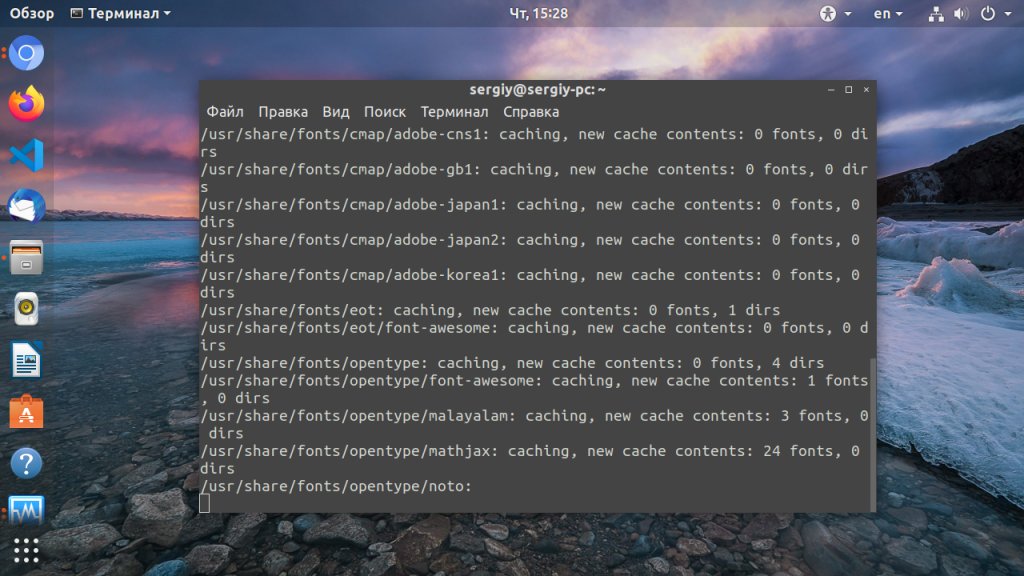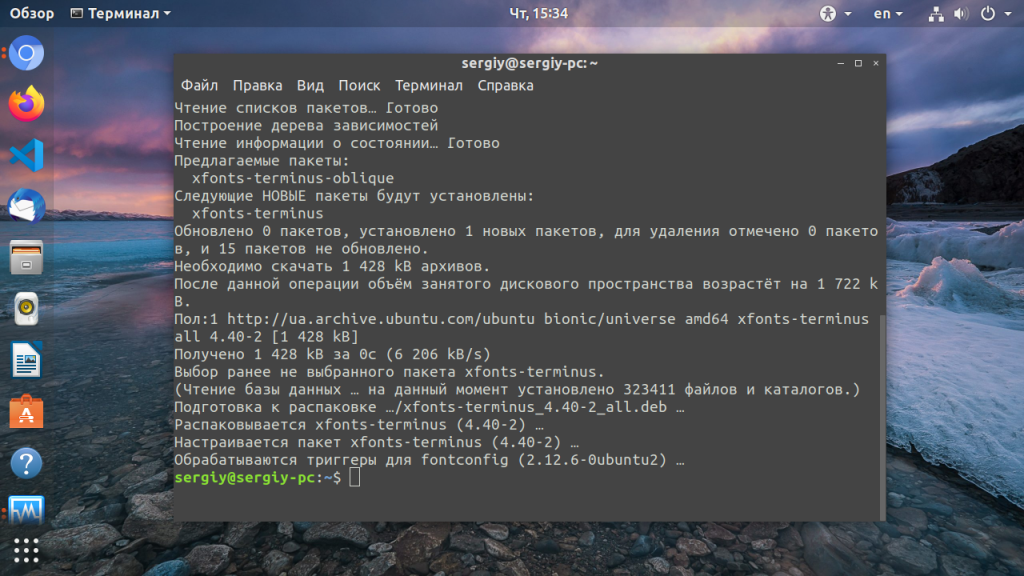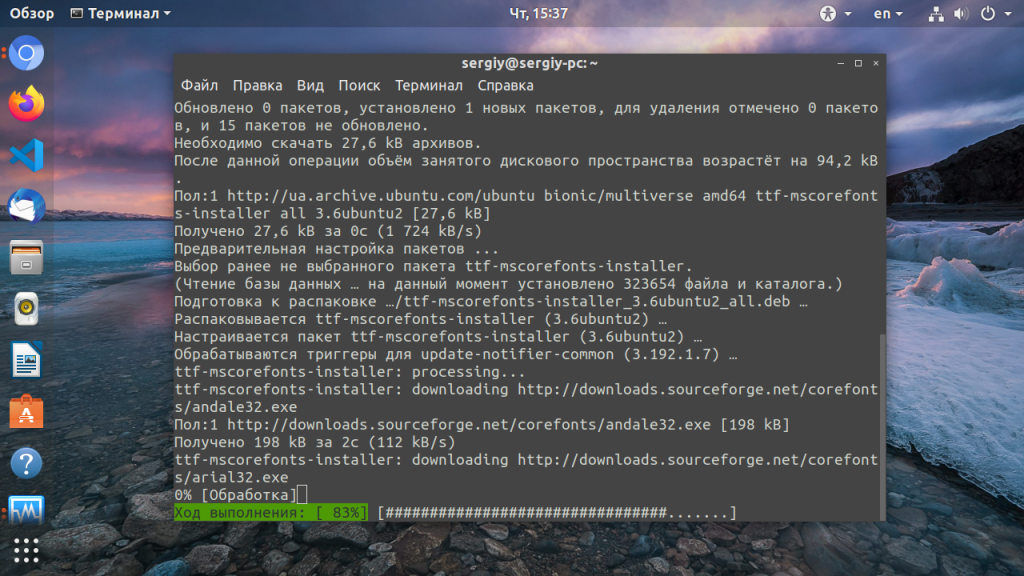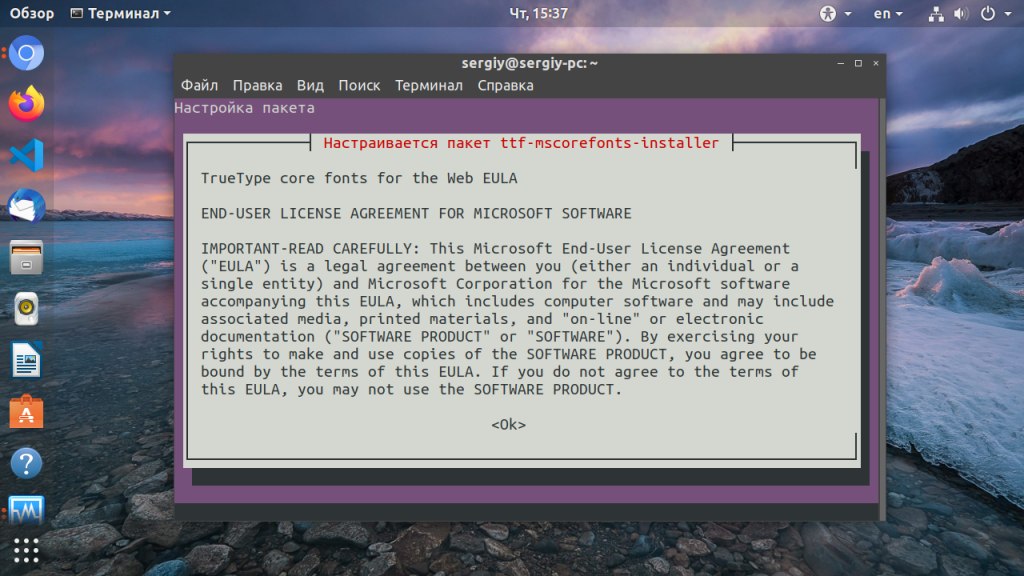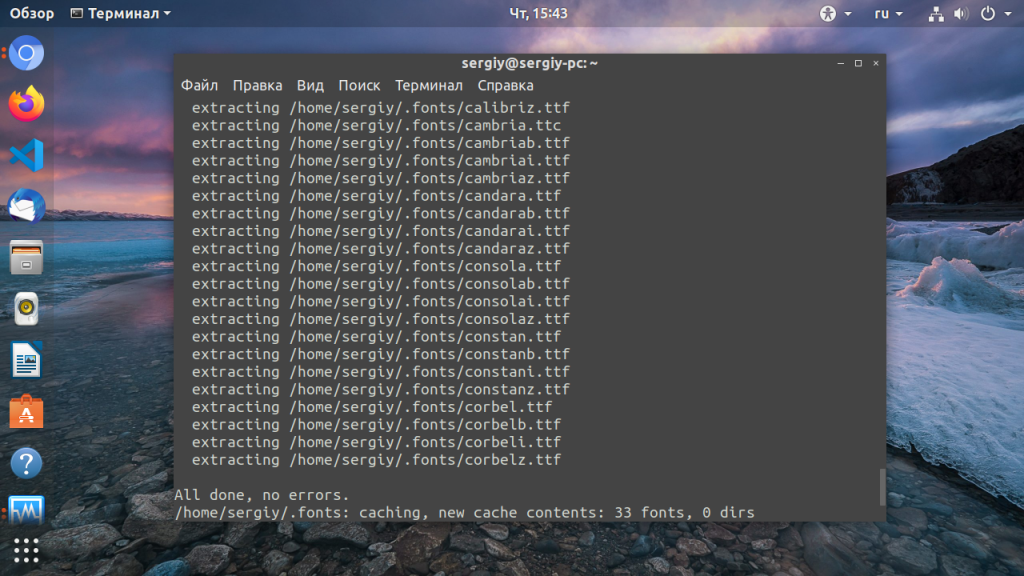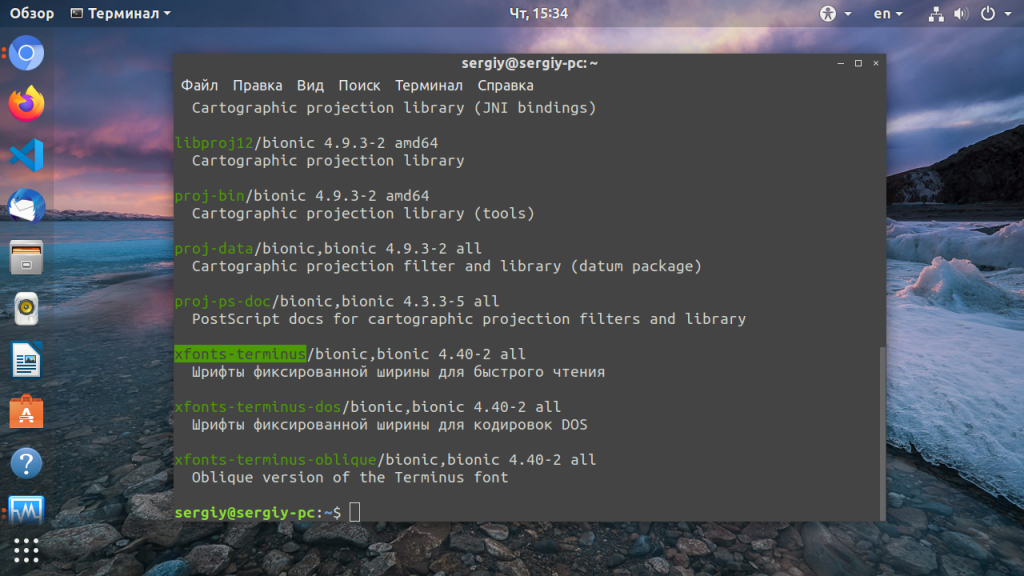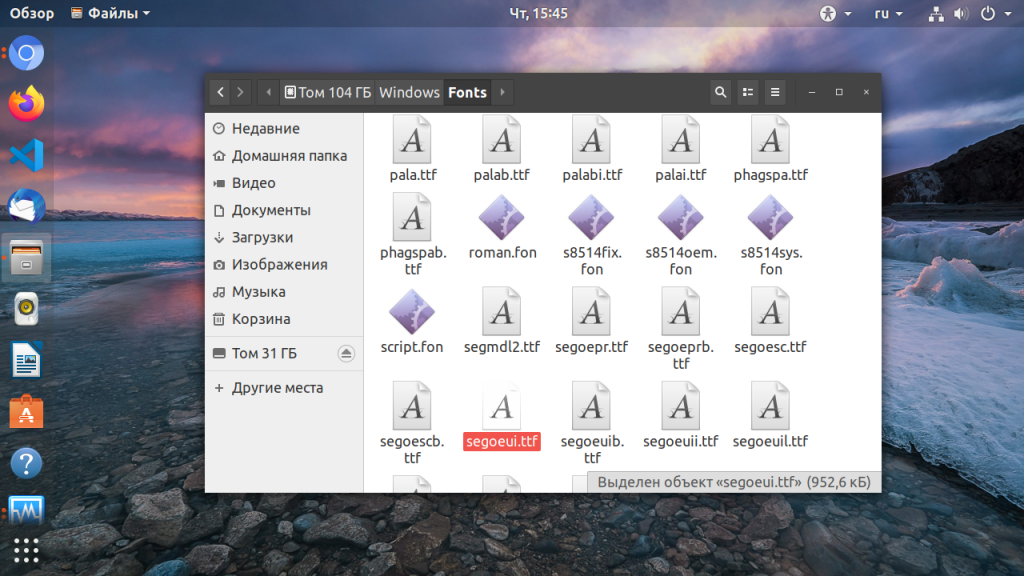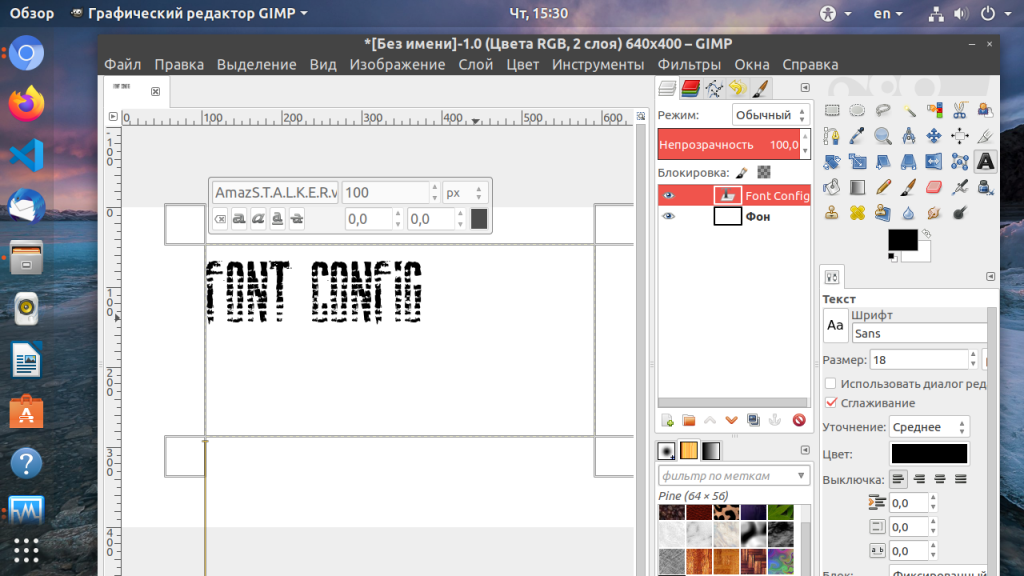
Установка шрифтов в Linux
Все мы хотим чтобы наша система выглядела идеально. Но не всегда поставляемые в дистрибутиве шрифты выглядят красиво, или хотя бы даже приемлемо. Вы можете очень просто установить и использовать любой понравившийся вам шрифт. С другой стороны, для работы с официальными документами в офисных приложениях нам нужны такие шрифты, как Times New Roman, Colibri и многие другие. Но эти шрифты разработаны корпорацией Microsoft и не могут быть включены по умолчанию в дистрибутив Linux.
В этой статье мы рассмотрим как происходит установка шрифтов в Linux на примере Ubuntu, как установить шрифт, который вам понравился, а также как поставить все шрифты от Microsoft, используемые в системе Windows.
Установка шрифтов в Linux
Шрифты можно найти на просторах интернета в различных форматах. В основном все шрифты можно поделить на два типа: растровые и векторные. Растровые шрифты быстрее и проще, но они не поддерживают масштабирование. В отличие от них векторные шрифты можно спокойно масштабировать без потери качества.
Вообще говоря, при работе со шрифтами вы, скорее всего, не заметите разницы растровый это шрифт или векторный, да и встречаются чаще всего только векторные шрифты.
1. Установка вручную
2. Установка с помощью пакетного менеджера
Установка шрифтов TrueType от Microsoft в Linux
Microsoft выпустила пакет основных TrueType шрифтов для веб-сайтов в 1996 году. Эти шрифты получили очень либеральную лицензию, поэтому их может установить любой желающий. Microsoft отдала их, потому что хотела чтобы они были стандартны во всех браузерах. Этот проект был закрыт еще в 2002 году, но установить и использовать их можно до сих пор.
Пакет содержит такие шрифты: Andale Mono, Arial, Arial Black, Comic Sans MS, Courier New, Georgia, Impact, Times New Roman, Trebuchet, Verdana, и Webdings. Times New Roman был шрифтом по умолчанию для всех документов, пока не вышел в 2007 году Collibri.
В Ubuntu выполните в терминале вот такую команду:
Перед тем, как начнётся установка шрифтов, вам нужно принять лицензию ELUA. Когда появится запрос лицензионного соглашения используйте стрелки вверх / вниз чтобы прокрутить его. Затем нажмите кнопку Tab чтобы переместить курсор на позицию Yes и нажмите Enter.
Только после этого начнётся установка шрифтов:
Таким образом, вы принимаете лицензионное соглашение Microsoft. Программа установки загрузит шрифты в вашу систему и сделает их сразу доступными для всех приложений. В других дистрибутивах установка шрифтов Linux отличается только менеджером пакетов.
Microsoft добавила группу новых ClearType шрифтов для Windows начиная с Windows Vista и Office 2007. Это такие шрифты, как: Constantia, Corbel, Calibri, Cambria, Candara, and Consolas. Collibri стал шрифтом по умолчанию в Office 2007.
Выводы
Теперь вы знаете как установить шрифты в Linux и сможете настроить свою систему так как нужно. Со шрифтами в документах все еще более просто. В Ubuntu да и в других дистрибутивах используется набор свободных шрифтов Red Hat, которые были разработаны для замены  Arial, Arial Narrow, Times New Roman и Courier New. Они имеют ту же ширину, что и шрифты от Microsoft. Поэтому если документ составлен с помощью Times New Roman, то в офисном пакете будет использоваться альтернативный шрифт из свободных шрифтов той же ширины, поэтому структура документа не будет нарушена. Поэтому устанавливать шрифты от Microsoft только ради просмотра документов совсем необязательно. Но выглядят они совсем не так как оригинал. Так что если вы хотите получить наибольшую совместимость с Microsoft Office желательно все же установить эти шрифты.